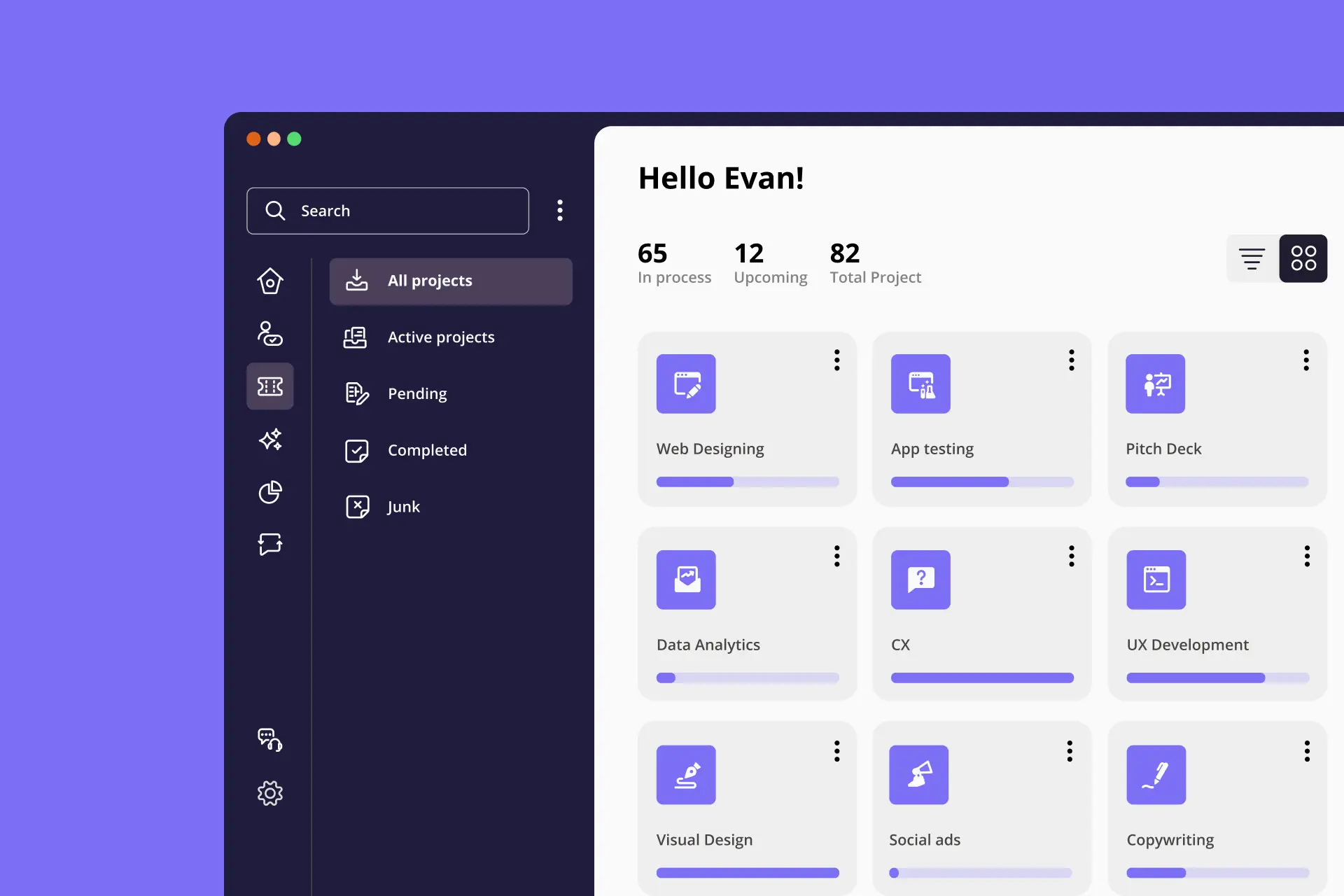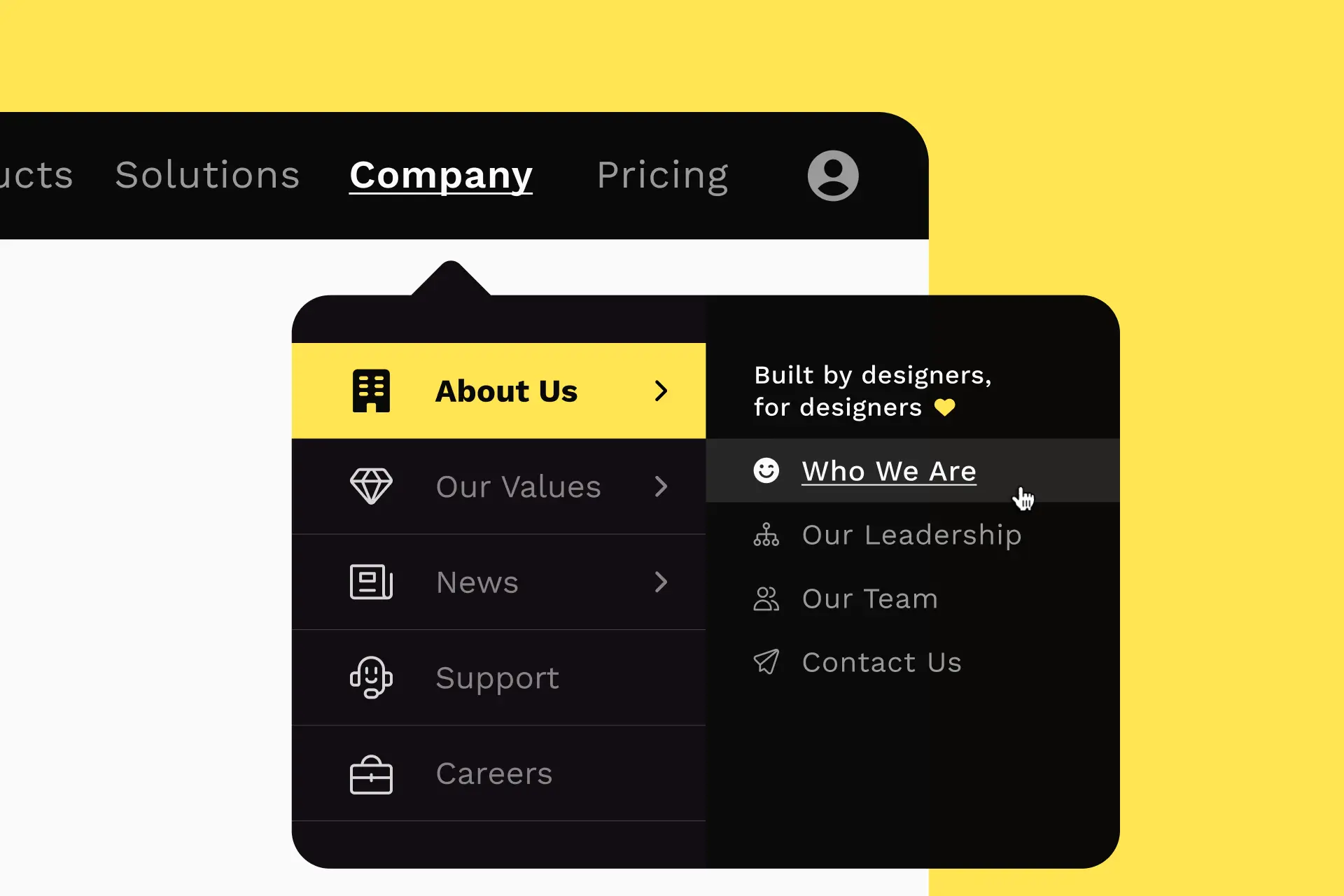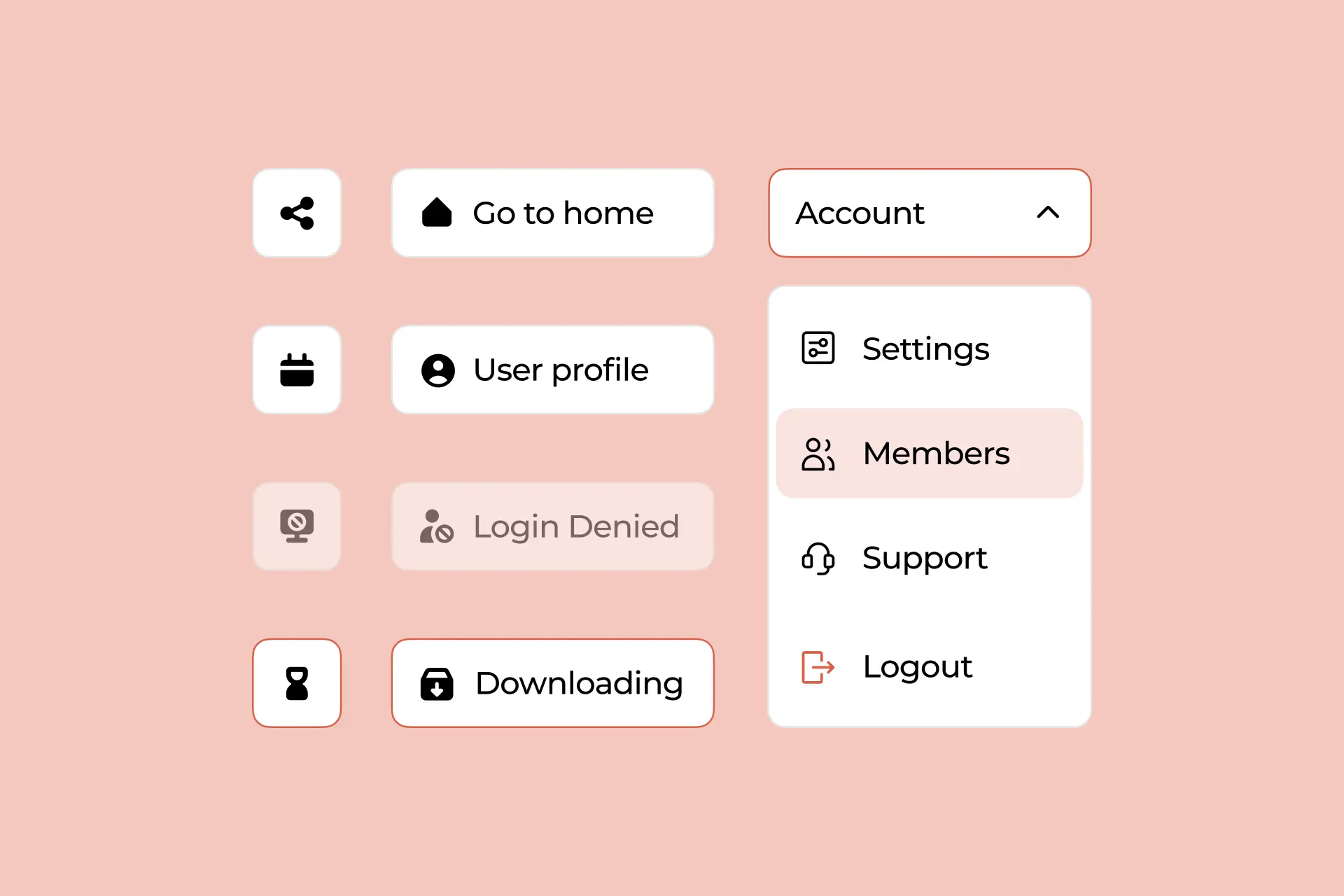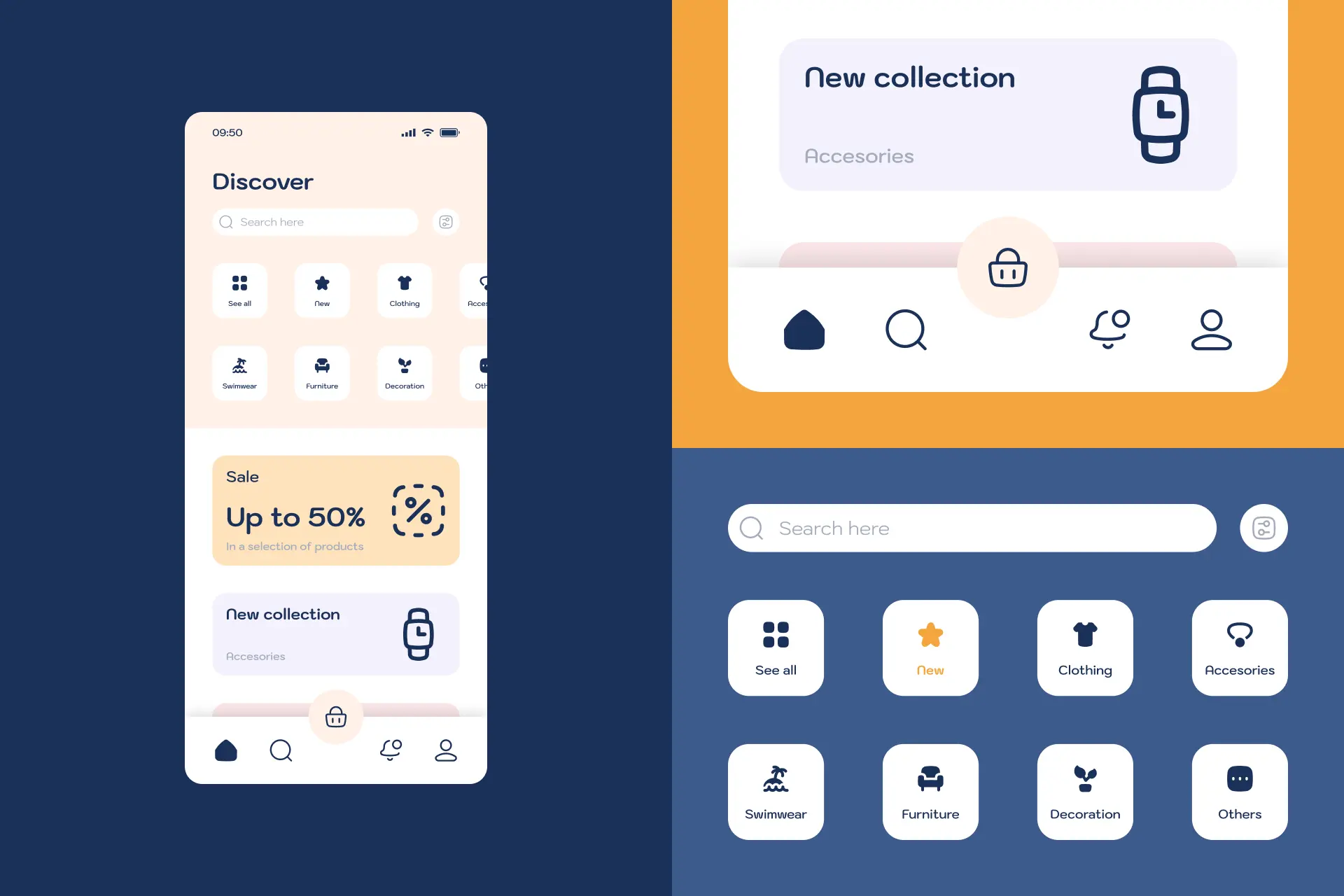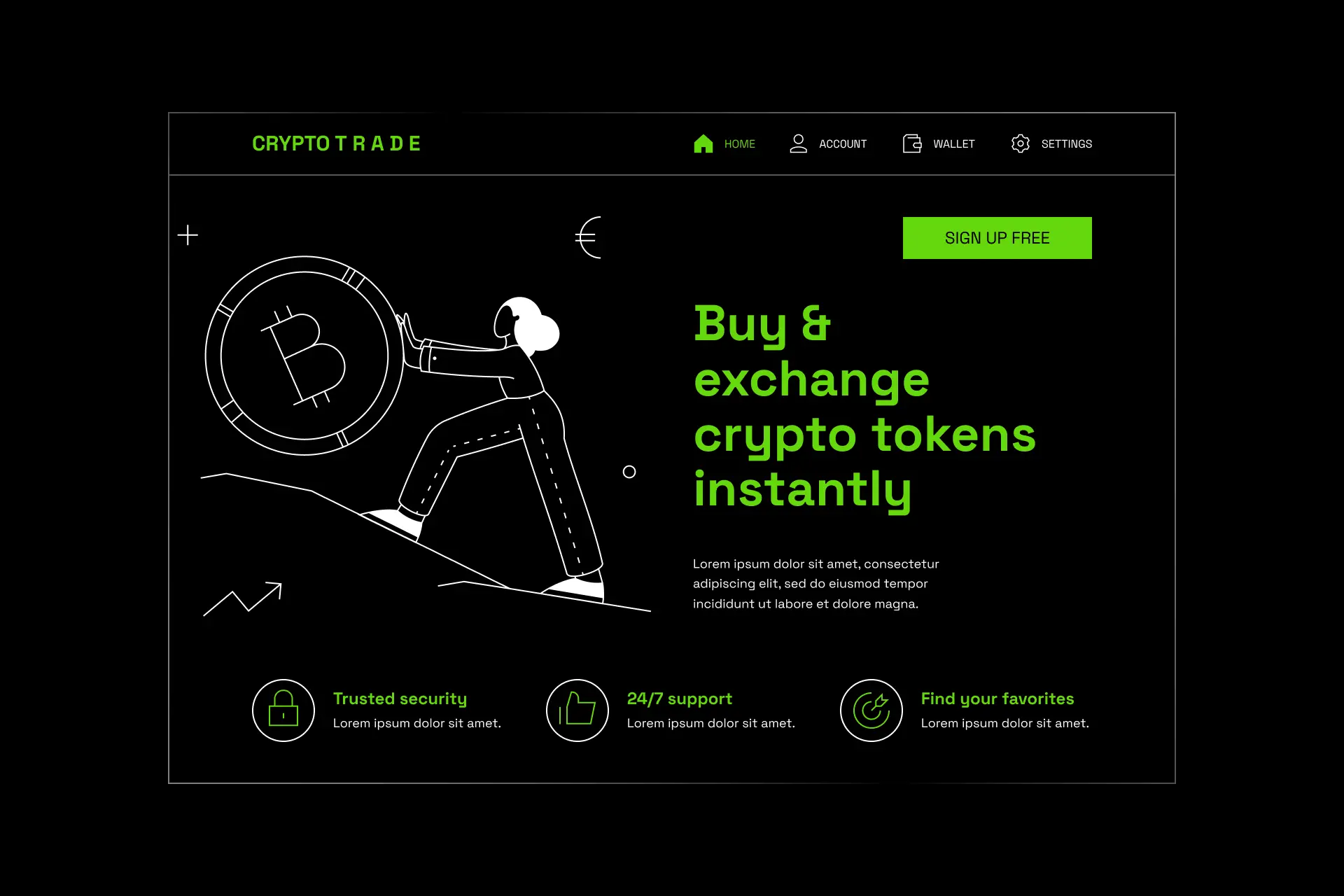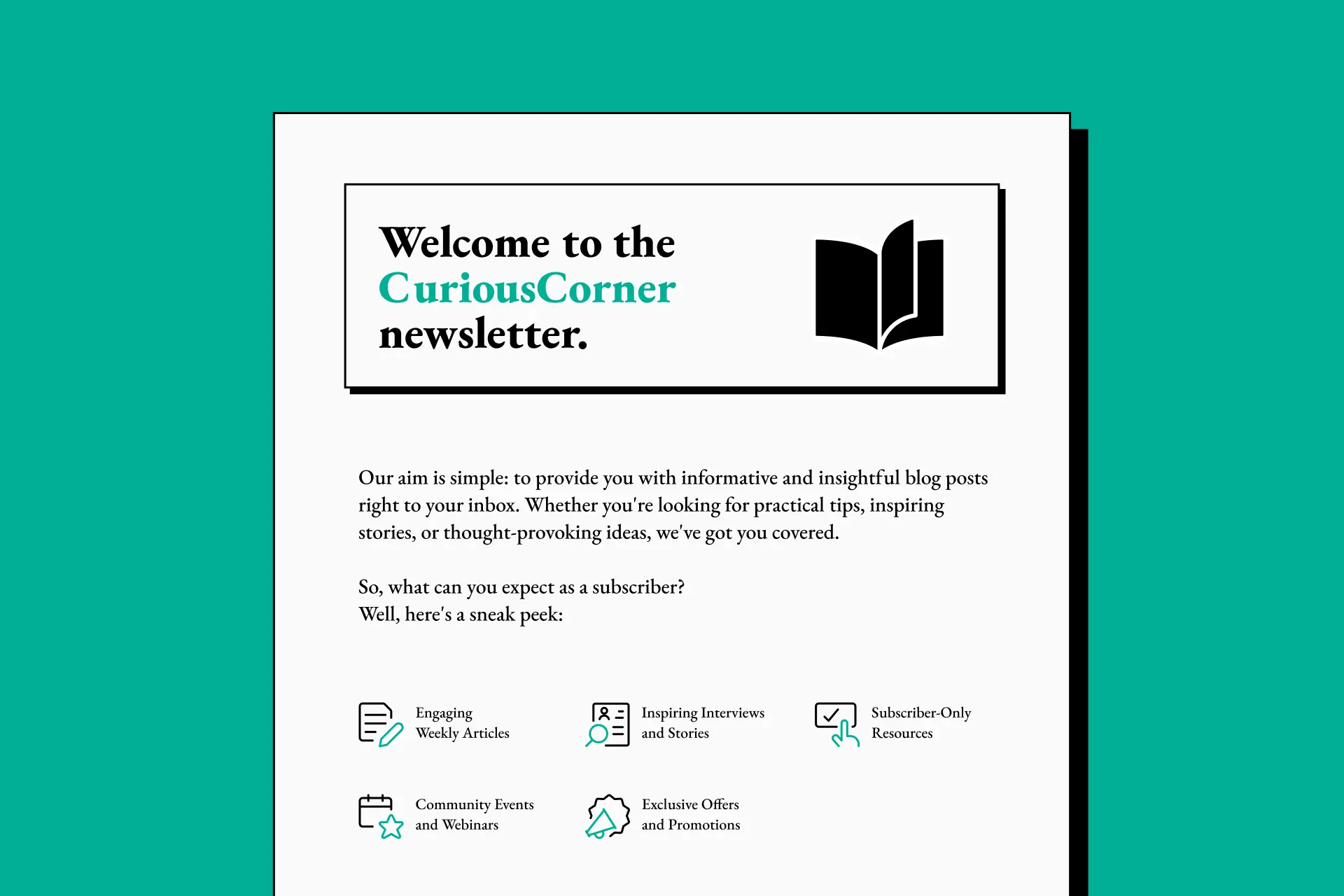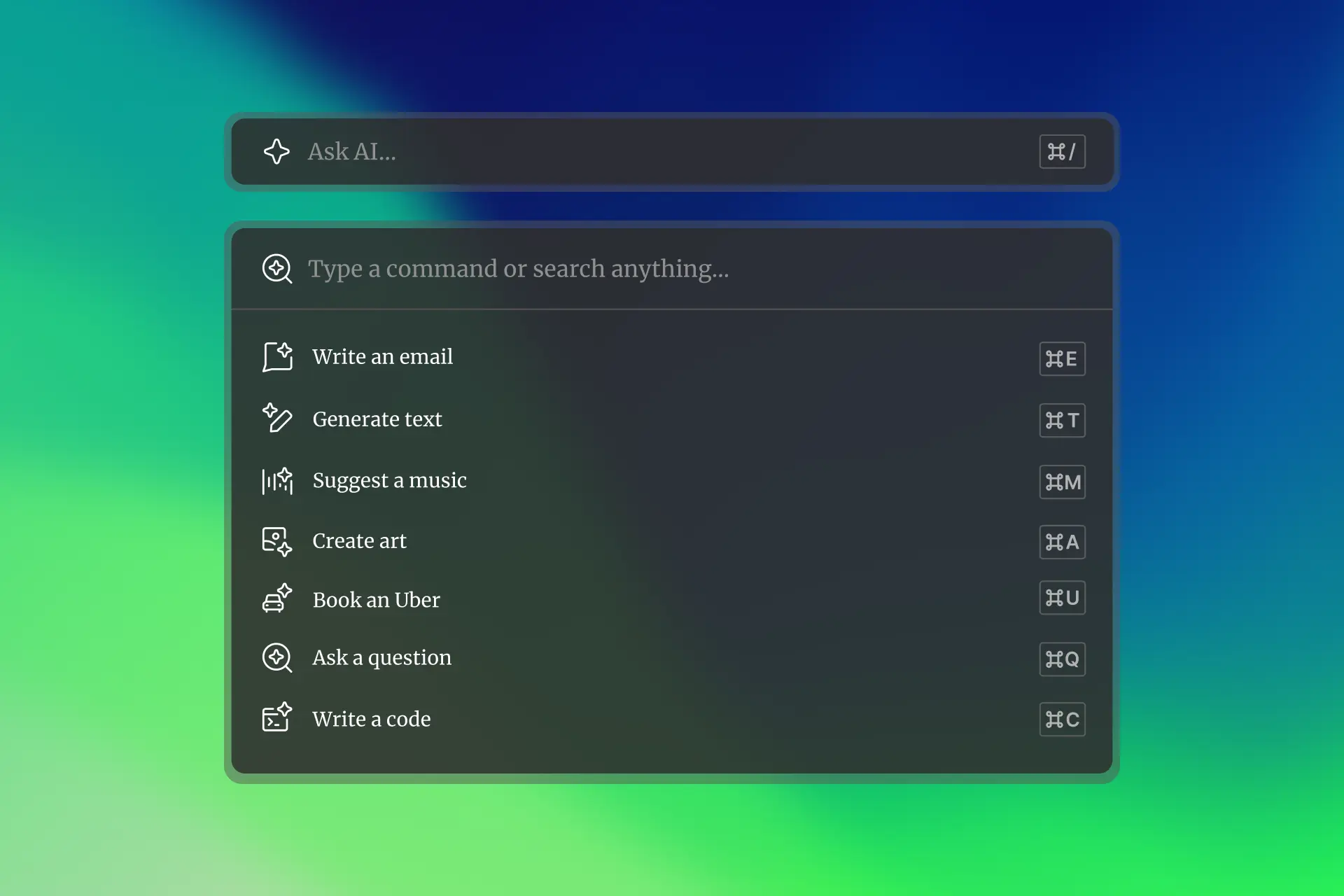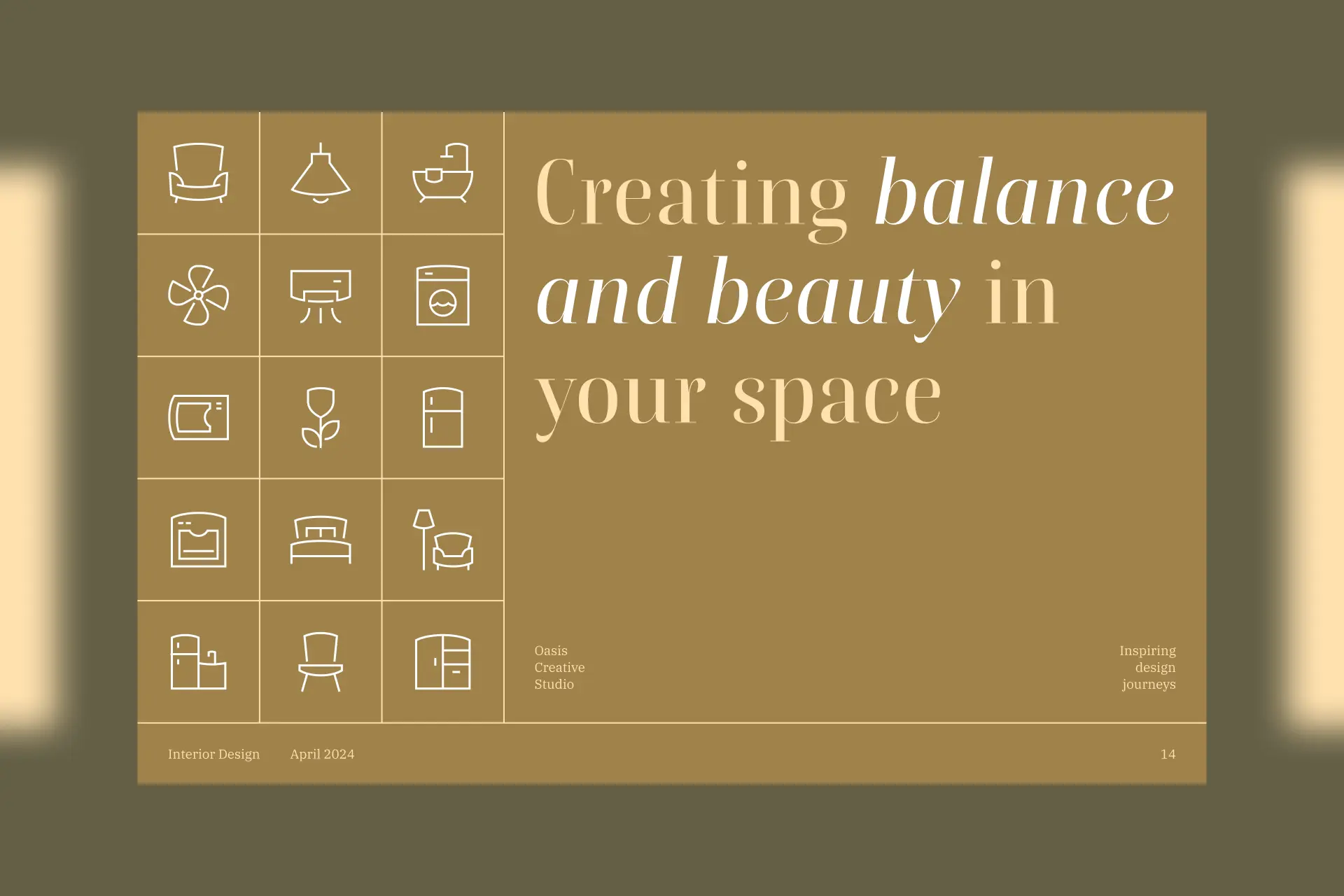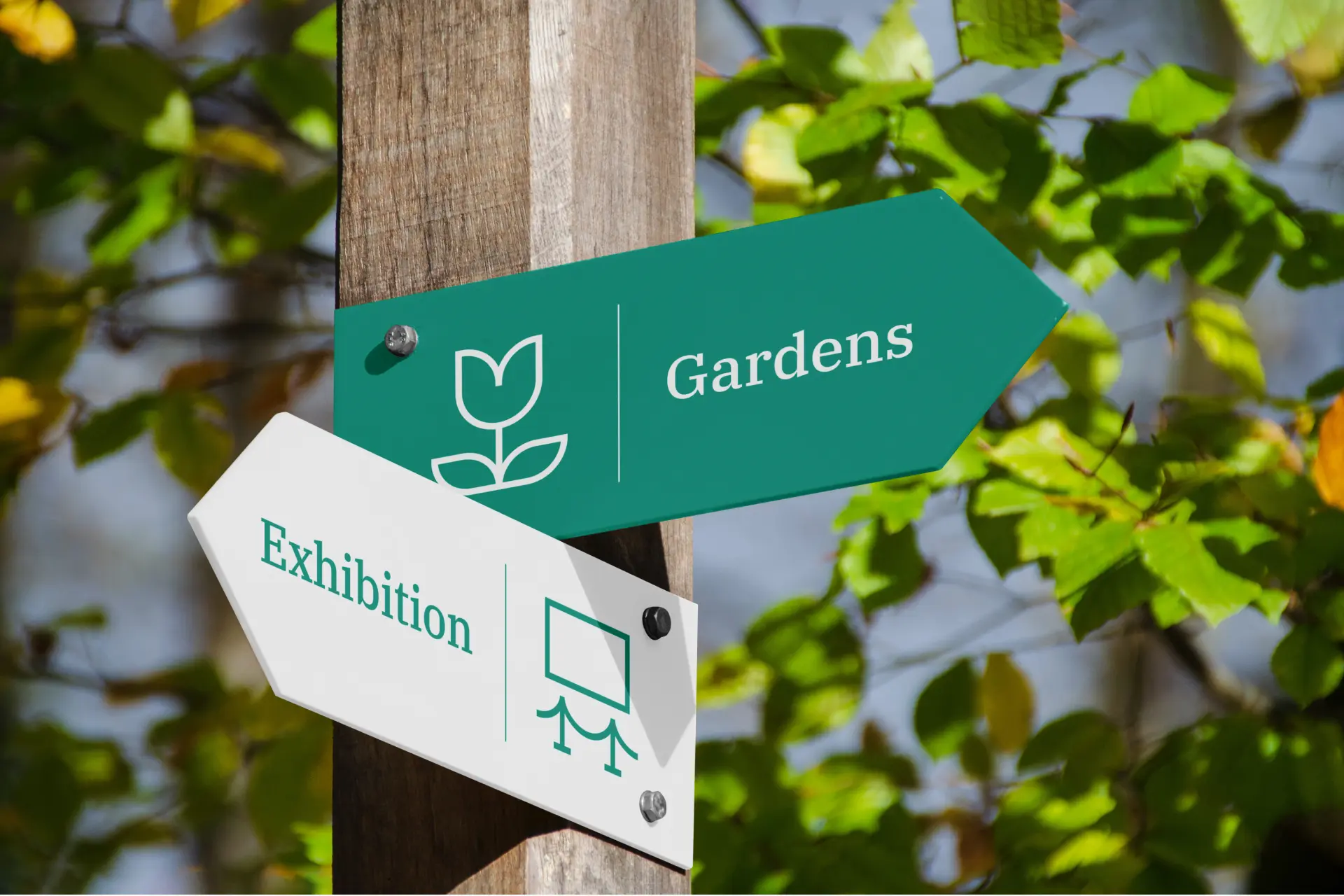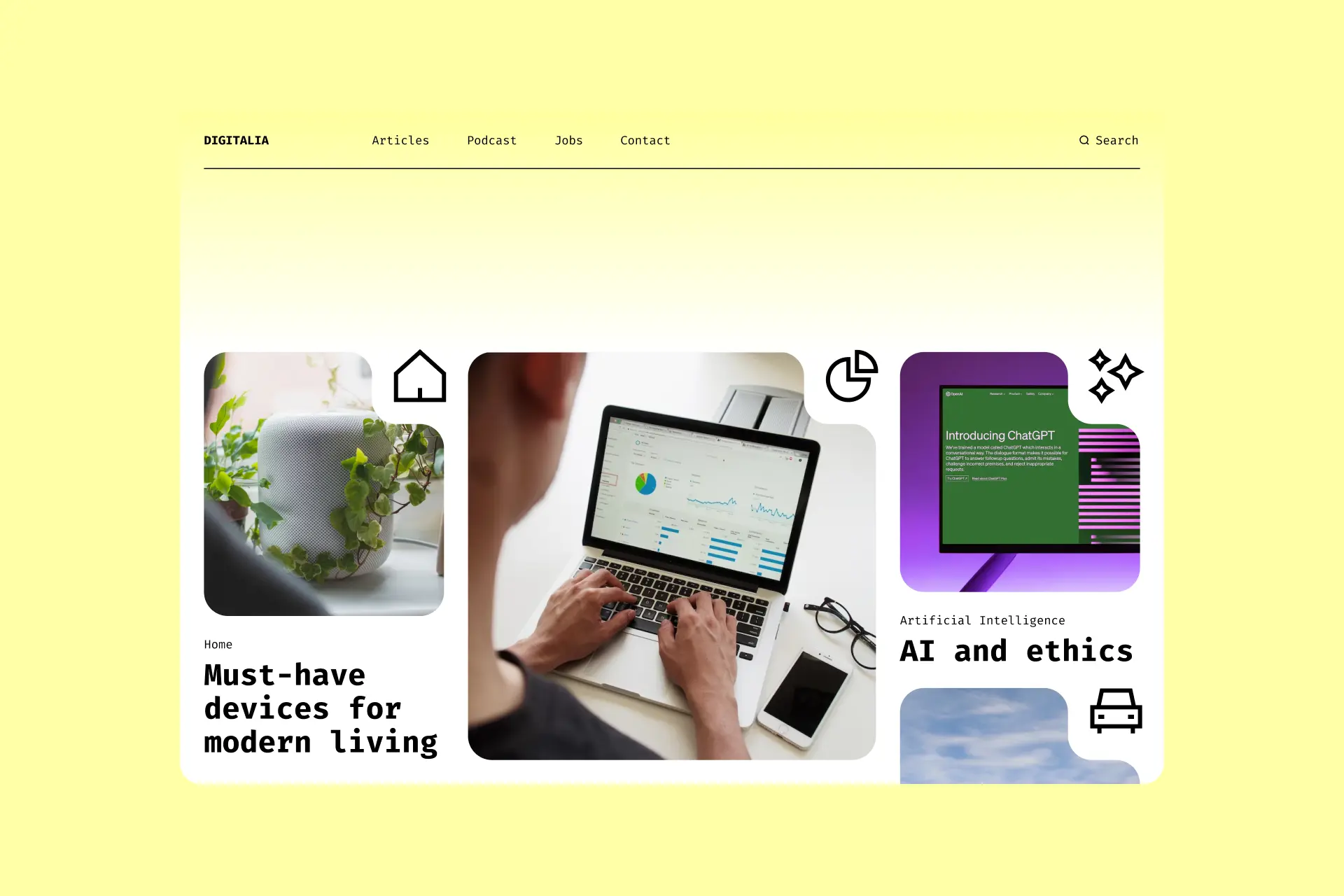
Як поєднувати шрифти та іконки в UI
Коротка інструкція, яка допоможе вам у виборі правильних іконок, спираючись на стандартну класифікацію шрифтів та їх анатомію.
Шрифти та іконки – два важливі компоненти інтерфейсу. Щоб ці елементи не конфліктували, а, навпаки, доповнювали та підсилювали один одного, варто дотримуватися кількох принципів, про які ми поговоримо у цій статті.
При виборі іконок, що доповнюють шрифт, враховуйте такі фактори:
- Мета та контекст. Хто ваша аудиторія? Яке повідомлення ви хочете донести? Яким має бути загальний тон проєкту? І шрифт, і іконки повинні відповідати цим концепціям.
- Стиль та естетика. Оцініть візуальний стиль проєкту та шукайте шрифти і іконки, які гармонійно вписуються в цю естетику.
- Масштабованість і адаптивність. Оцініть масштаб проєкту та контекст, у якому мають використовуватися іконки. Можливо, вам знадобляться іконки в кількох стилях або з різними характеристиками (наприклад, різна товщина обведення).
Шрифти без засічок
Шрифти без засічок виглядають лаконічно та акуратно, що робить їх популярними у цифрових інтерфейсах та графічному дизайні.
Для таких шрифтів підходять чисті, прості і сучасні іконки, основані на мінімалістичних і розбірливих формах.
Прикладом може слугувати набір іконок Ultimate, який містить велику кількість нейтральних іконок у різних стилях (Light, Regular, Bold, Duotone та Colors). Усі вони ідеально гармонують із гротесками.
Відмінна комбінація - іконки Ultimate і Open Sans , гуманістичний гротеск з об'ємними контрформами, що відрізняється високою читабельністю. Альтернативні варіанти: Noto , Lato , Gill Sans .
Інший схожий набір іконок - Core . Іконки представлені в чотирьох стилях (Line, Solid, Duo та Flat), вони здаються ще більш простими та універсальними. Завдяки своїй вражаючій адаптивності такі іконки ідеально поєднуються зі шрифтами без засічок.
Іконки Core чудово виглядають у комбінації з Work Sans, шрифтом, який був створений на основі ранніх гротесків і має 10 написів, що забезпечує максимальну гнучкість. Якщо цей шрифт вам не до смаку, ви також можете придивитися до Inter , Roboto або Neue Haas Grotesk .
Однак, якщо вам потрібен набір іконок, який буде працювати в найменшому масштабі, зверніть увагу на Micro. Він має ті ж базові характеристики, що і Core, але побудований на основі дрібнішої сітки і, отже, відрізняється меншим рівнем деталізації та підвищеною розбірливістю.
У цьому випадку відмінною парою буде більш геометричний шрифт із широкими літерами, такий як Montserrat . Альтернативні варіанти: Poppins , Raleway або Gotham.
Шукаєте щось яскравіше та характерніше? Пропонуємо – Flex . Ці "живі", розгорнуті та елегантні іконки не залишать байдужим нікого. Щоб створити гармонійну пару, обирайте шрифт з округленими кінцями штрихів і великою кількістю кривих.
Шрифт Kodchasan - напрочуд підходящий партнер для Flex. Таке відчуття, ніби вони були побудовані на основі тих самих принципів. Є й більш нейтральні альтернативи: Rubik , Nunito , Noway Round.
Якщо ж вам подобаються суворіші, «архітектурні» гротески, чудовим варіантом буде Sharp. Іконки з цього набору виглядають геометричними та грубуватими.
Такому брутальному набору іконок потрібен агресивний шрифт, наприклад, Space Grotesk — унікальний, але при цьому розбірливий гротеск у стилі hi-tech. Інші варіанти: DM Sans , Archivo , Neue Machina.
Шрифти із засічками
Шрифти із засічками виглядають більш формально та традиційно. Їх часто можна зустріти у книгах, газетах та журналах.
З такими шрифтами поєднуються елегантні іконки з вишуканими деталями та помірним контрастом.
Хороше рішення – вже розглянуті набори Ultimate та Core. Вони досить універсальні і не відволікатимуть надто багато уваги від основного контенту.
У випадку з Ultimate для створення «традиційного» візуалу підійде антиква старого стилю, наприклад, EB Garamond . Альтернативні варіанти: Cormorant , Cardo , Sabon.
Що стосується Core, то з ним найкраще виглядатиме перехідна антиква (що поєднує в собі ознаки антикв старого і нового стилю), наприклад, Merriweather , з її вищим контрастом і симетричними гліфами. Така комбінація, незважаючи на свою серйозність, виглядатиме досить сучасно. Інші можливі варіанти - Domine , Spectral або Signifier.
Однак існують набори іконок, які спочатку були задумані для використання у парі з антиквами. Наприклад, Platinum було розроблено спеціально для люксових брендів. Його відрізняють тонкі штрихи, увігнуті криві та гострі кути, які надають йому елегантного та класичного вигляду.
Platinum — універсальний набір іконок, ніж може здатися на перший погляд. Контрастні шрифти із засічками, такі як Boska , ідеально поєднуються з ним завдяки властивій їм витонченості. Якщо вам подобається цей стиль, також зверніть увагу на Prata , Marcellus та Domaine.
Набір іконок Guidance – рідний брат Platinum, але тут опуклі криві поступаються місцем увігнутим. Вони створюють сильний контраст із прямими лініями.
Звичайно, іконки можна створити самостійно на основі шрифту, проте це потребує певних технічних знань та навичок. Успішні приклади такого підходу: іконки, розроблені Даніелем Утцем для шрифту Netto, а також набір іконок для вивісок аеропорту Кельн/Бонн.
Отже, шрифти та іконки є частиною єдиної візуальної мови. Вони базуються на спільних принципах і є необхідними для створення цілісного, гармонійного дизайну. Уважно аналізуючи основні характеристики цих елементів, ви зможете створювати вражаючі, позачасові поєднання.